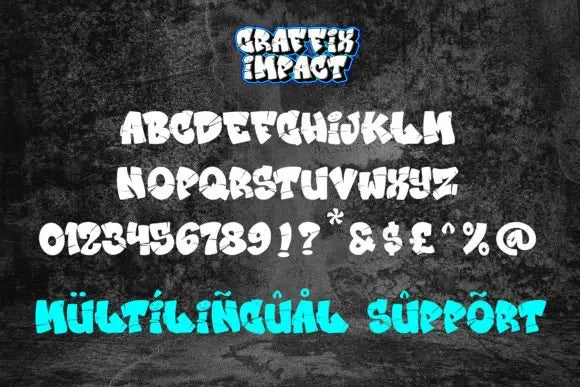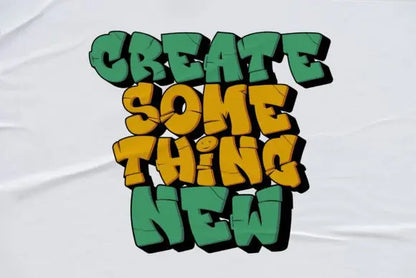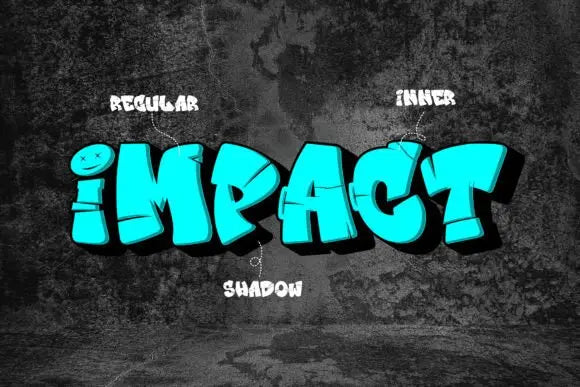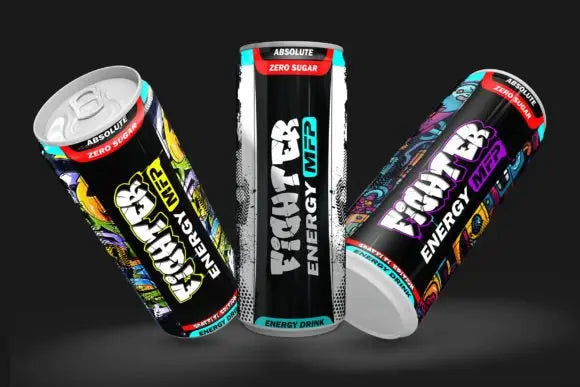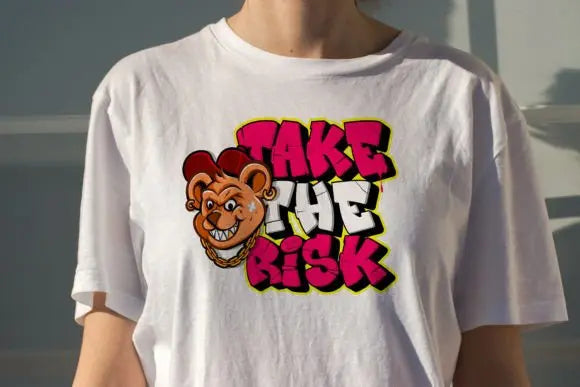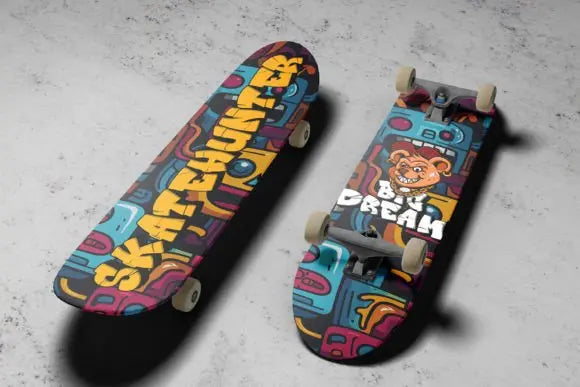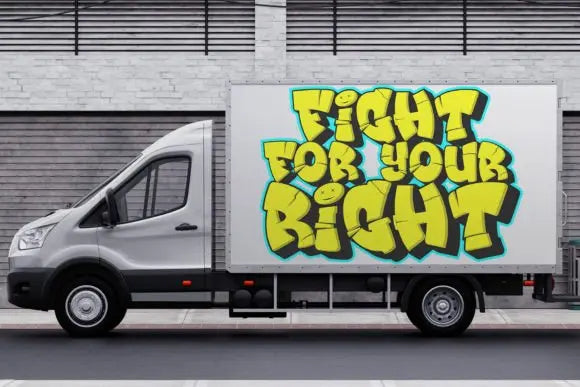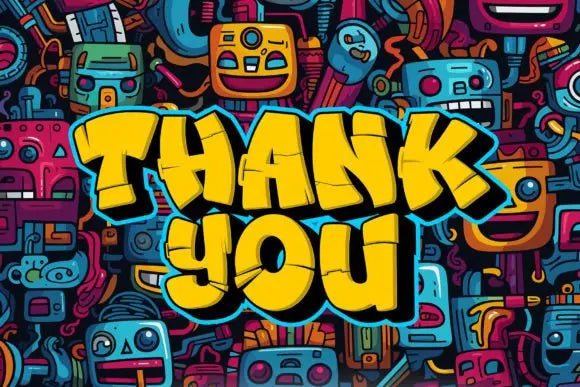
Fuente de impacto Graffix
Graffix Impact” es una fuente de graffiti en capas 3D que incluye una ruptura o interrupción dentro de los caracteres. Fuentes como esta ofrecen una apariencia tridimensional al emplear múltiples capas para crear profundidad y dimensionalidad. La “ruptura” en los personajes puede introducir un elemento estilístico, mejorando el impacto visual general.
El uso de “Graffix Impact” le permite incorporar un estilo de texto único y visualmente impactante con un efecto tridimensional y saltos de caracteres.
Esta fuente es adecuada para diversas aplicaciones de diseño, especialmente aquellas que buscan un aspecto tipográfico audaz y dinámico, como en graffiti, carteles o diseños donde se requiere un texto visualmente cautivador.